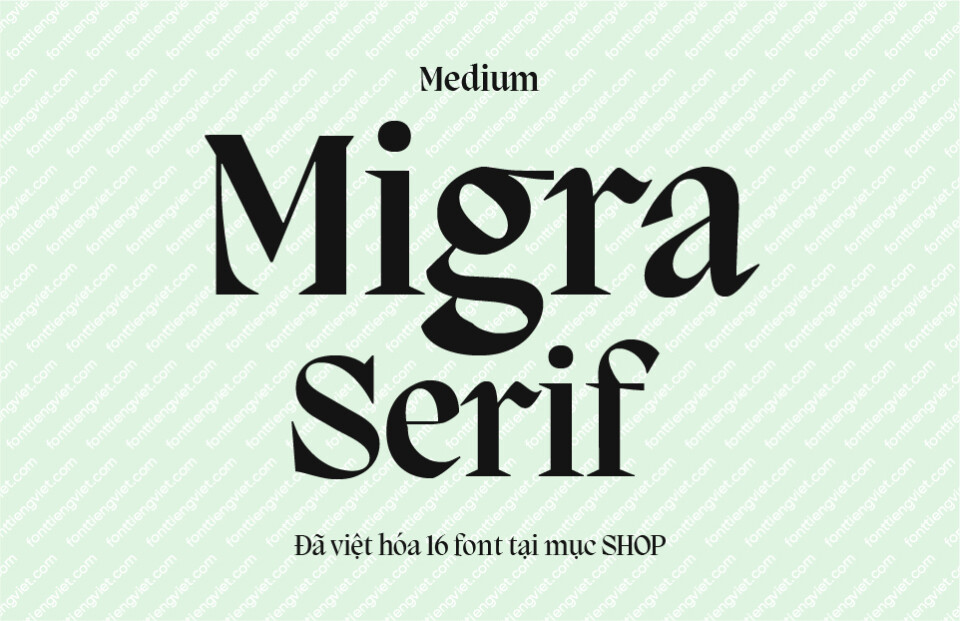
Font Việt hóa 1FTV VIP Migra Medium
Giới thiệu về Font Việt hóa 1FTV VIP Migra Medium
Trong thế giới thiết kế đồ họa hiện đại, việc lựa chọn một bộ font chữ phù hợp đóng vai trò quyết định đến tính thẩm mỹ và sự thành công của một tác phẩm. Font Việt hóa 1FTV VIP Migra Medium là một trong những bộ font đang nhận được sự quan tâm rất lớn từ cộng đồng designer tại Việt Nam. Đây là một phông chữ Serif mang phong cách thanh lịch, hiện đại nhưng vẫn giữ được nét cổ điển đặc trưng. Khi sử dụng Font Miễn Phí để sáng tạo các ấn phẩm học đường hay trang trí bài giảng, các bạn học sinh và thầy cô giáo sẽ cảm nhận được sự tinh tế mà nó mang lại cho từng con chữ.
Tại sao nên lựa chọn Font Việt hóa 1FTV VIP Migra Medium cho thiết kế
Đặc điểm thiết kế độc đáo
Font Việt hóa 1FTV VIP Migra Medium nổi bật với những đường nét uốn lượn sắc sảo cùng độ tương phản giữa các nét thanh và nét đậm một cách hài hòa. Phiên bản Medium này mang lại cảm giác chắc chắn, dễ đọc, phù hợp cho cả tiêu đề lẫn nội dung văn bản ngắn. Điểm đặc biệt của bản 1FTV VIP là hệ thống dấu tiếng Việt được trau chuốt tỉ mỉ, giúp văn bản không bị lỗi hiển thị hay nhảy chữ khi gõ văn bản có dấu phức tạp.
Tính ứng dụng đa dạng trong học tập và công việc
Đối với các bạn học sinh, việc dùng Font Việt hóa 1FTV VIP Migra Medium trong các bài thuyết trình PowerPoint hay thiết kế bìa báo tường sẽ giúp nội dung trở nên nổi bật và chuyên nghiệp hơn. Trong môi trường nhà trường, các thầy cô có thể ứng dụng font này để tạo ra các bảng tin hoặc thiệp mời sự kiện mang tính trang trọng. Sự kết hợp giữa nét chữ nghệ thuật và tính ứng dụng cao giúp Migra Medium trở thành lựa chọn hàng đầu cho các dự án đòi hỏi sự chỉn chu về mặt hình ảnh.
Lưu ý khi phối hợp font chữ
Khi sử dụng Font Việt hóa 1FTV VIP Migra Medium, bạn nên kết hợp nó với một font không chân (Sans-serif) đơn giản để tạo ra sự cân bằng cho bố cục. Việc này giúp người xem không bị rối mắt và tập trung hơn vào những thông điệp quan trọng nhất mà bạn muốn truyền tải qua thiết kế của mình.
Kết luận về giá trị của bộ font